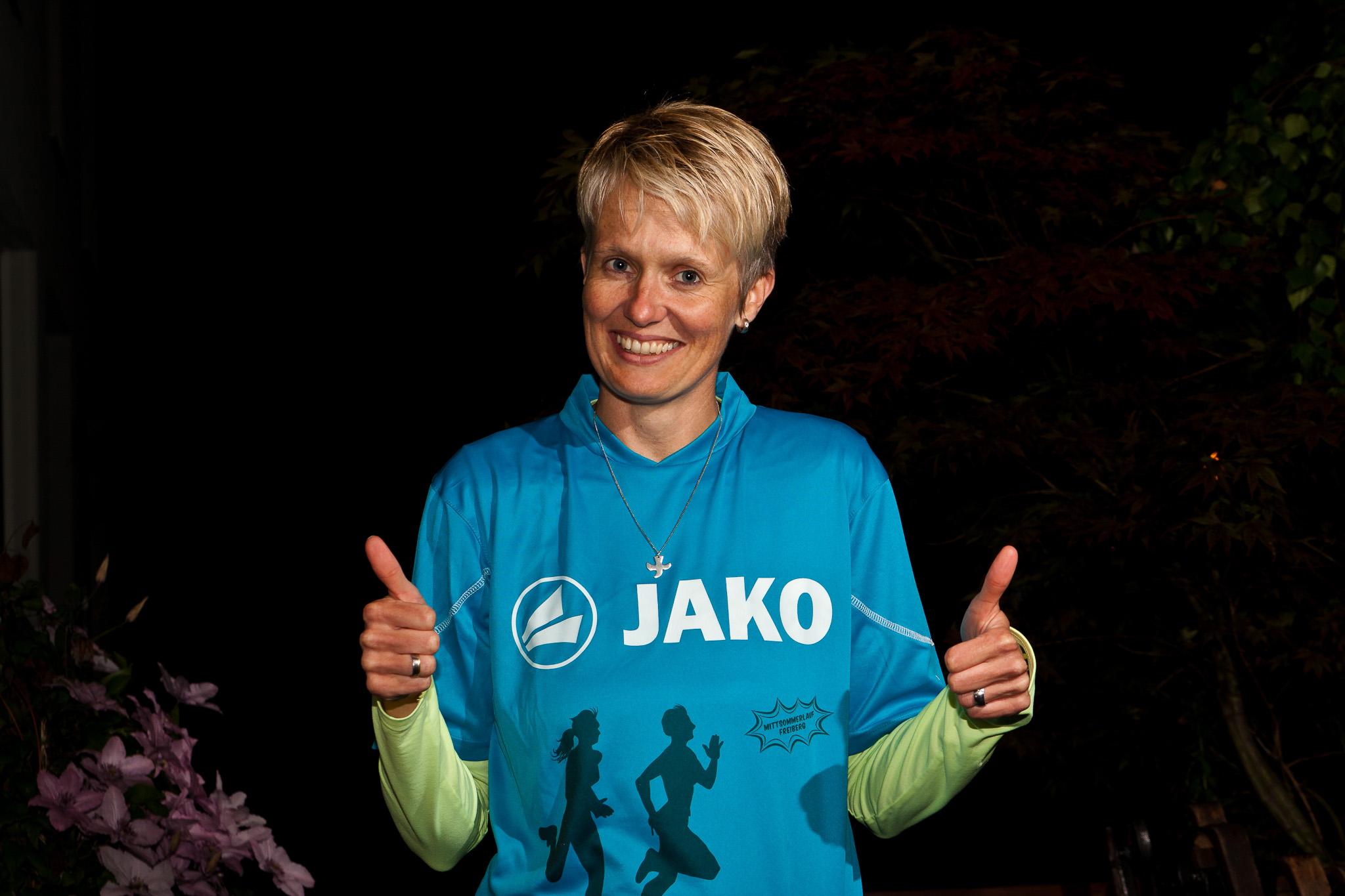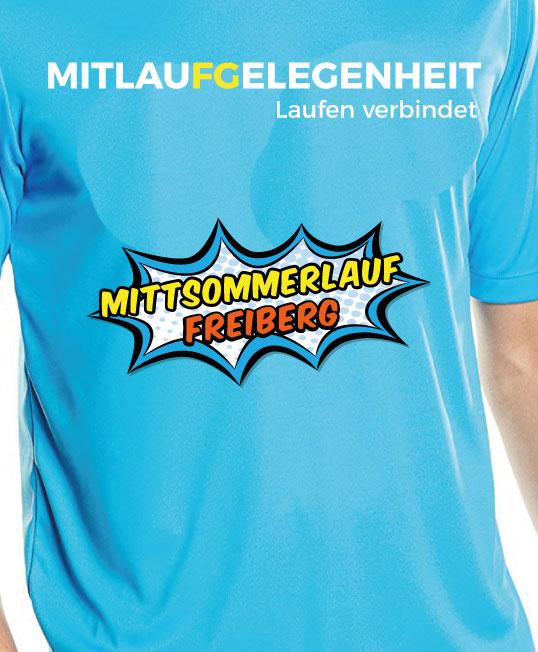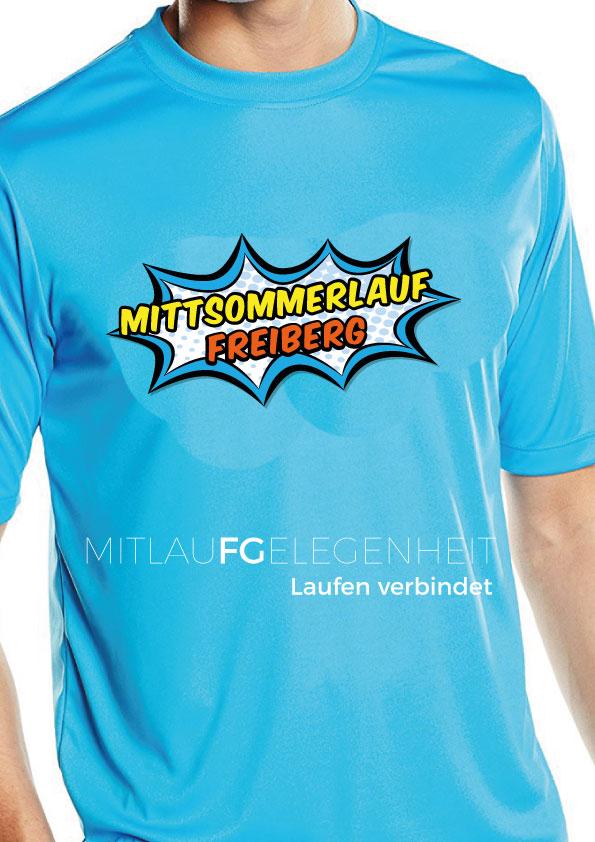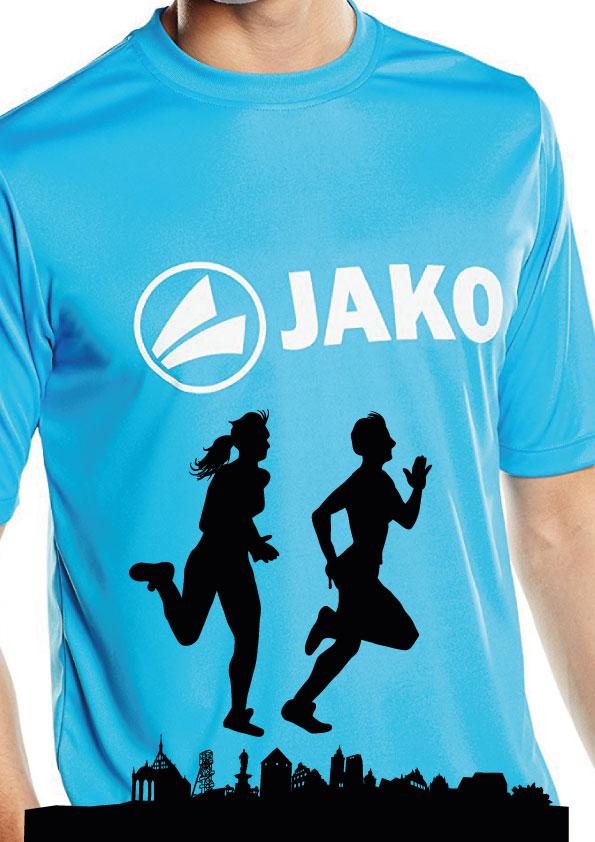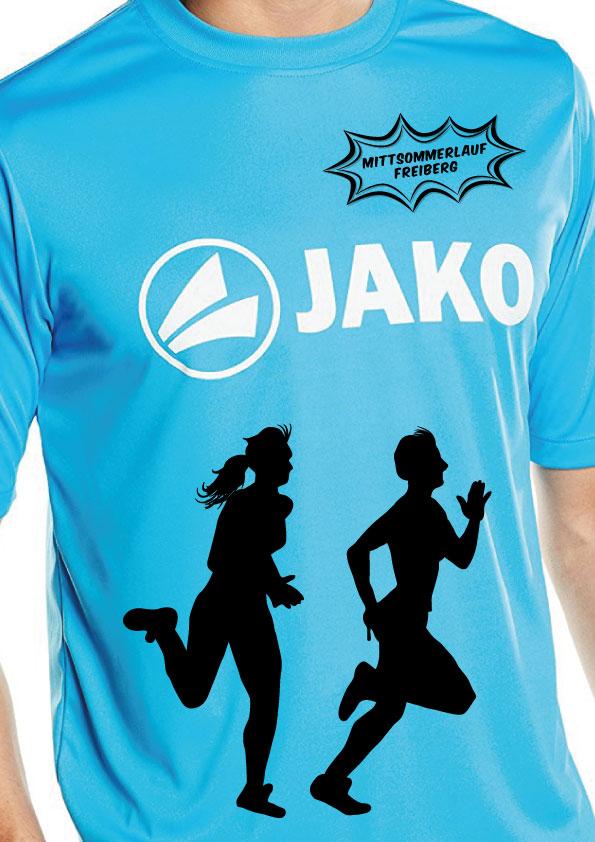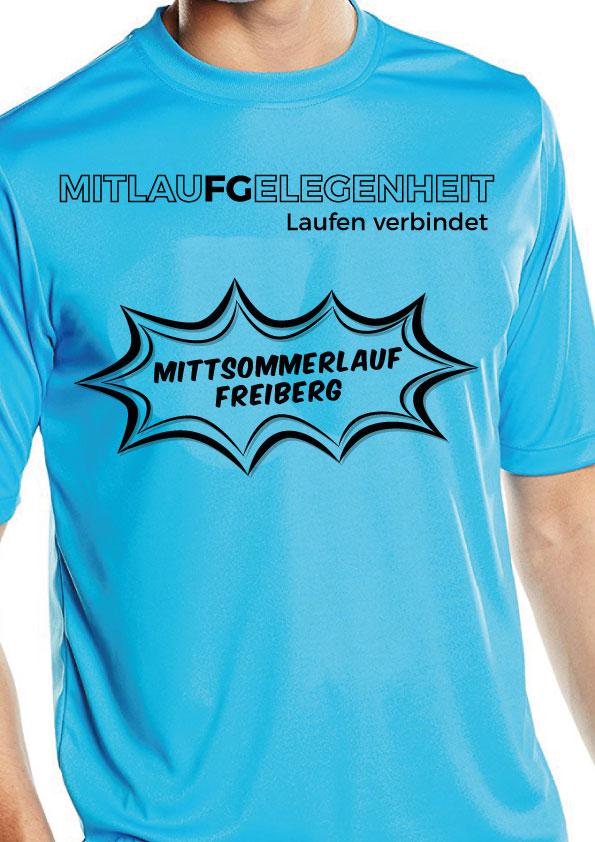
Schrift Midsummer Half
Wir wollen aus Refugee-Lauftreff Freiberg jetzt "Miflaufgelegenheit" mit dem Zusatz "Laufen verbindet" machen.
zuück zum Thema :-)  Wir haben keine weißen T-Shirts mehr bzw. nicht mehr genug in den richtigen Größen aber dafür diese hellblauen hier und ich hoffe das geht auch mit dem Druck ...  Entwurf für die Vorderseite in 2 Versionen. Die Rückseite kommt gleich  ...
Wenn's kostenmäßig geht, schwarze Läufer und weiße Schrift. Macht mehr her.
Wenn's kostenmäßig geht, schwarze Läufer und weiße Schrift.
Die Druckerei kommt uns da sehr entgegen und deshalb ist auch der Farbdruck mit dem Mittsommer möglich ...
Die Rückseite
Falls das Blau so hell ist, wäre die dünne Schrift schwer zu erkennen (vor allem, wenn sich die Träger auch noch bewegen, was sie wohl tun). "FG" würde ich darum lieber farbig absetzen – und alles in bold.
So, klappt so alles nictht aber es wird auch so gehen ...  Auf weiß ist mit dem Druckverfahren alles möglich, auf anderen Farben leider nicht. Die andere Möglichkeit ist zeitlich nicht mehr zu schaffen und zu aufwendig und teuer.
Also bleiben nur Farben die dunkler sind als das hellblau und auch die Explosion mit "Mittsommerlauf" geht so nicht.
Habt ihr mit diesen Vorgaben noch Ideen? Wichtig ist das Mitlaufgelegenheit - Laufen verbindet, damit jeder sieht wer das organisiert hat und Ansprechpartner ist, dann Mittsommerlauf (als Schriftzug) und die Läufer.
Dann würde ich's vielleicht einfach pur schwarz (-weiß) machen – falls andere Farben mit dem Blau des T-Shirts "mischen".
Für das "Mitaufgelegenheit": Alle Buchstaben Outline außer FG (die solide).
Die "Explosion" einfach nur als schwarze Outline, also alle Farben raus.
Für das "Mitaufgelegenheit": Alle Buchstaben Outline außer FG (die solide).
Kannst Du mir das bitte noch kurz erläutern. Ich komme mit den Begriffen nicht klar.
Wenn du um die "leeren" Buchstaben außen ein Kontur anlegst, solltest du das auch bei den beiden "vollen" Buchstaben tun, sonst wirken diese kleiner als der Rest. Wenn's zu spät ist, ist’s auch nicht schlimm, in diesem Zusammenhang wird es niemandem aufstoßen – einfach beim nächsten Mal berücksichtigen, wenn's kein bewegtes T-Shirt ist.
Es ist wahrscheinlich schon im Druck, aber …